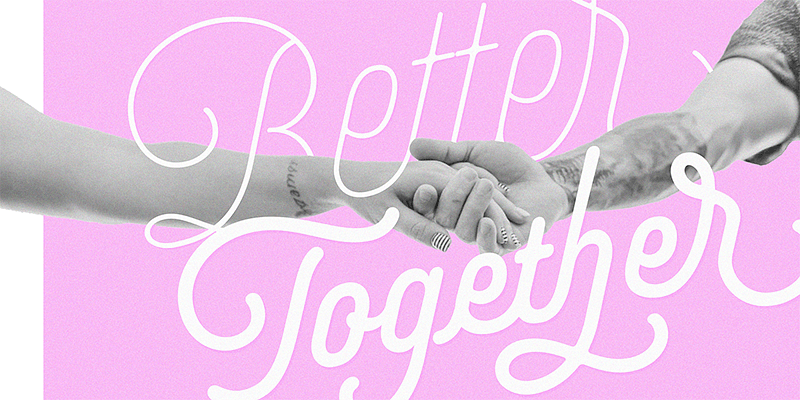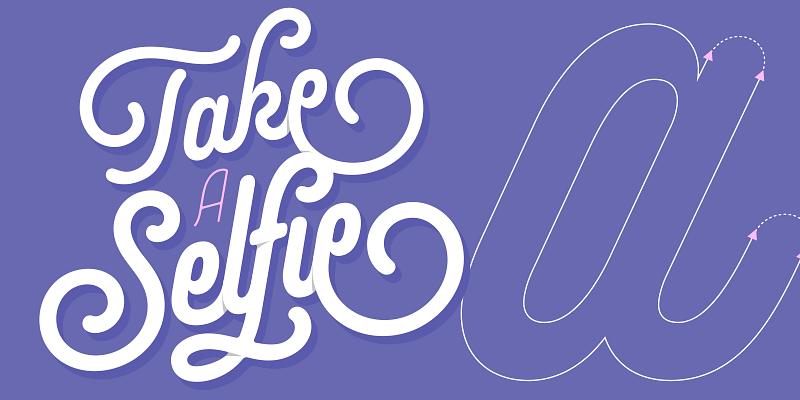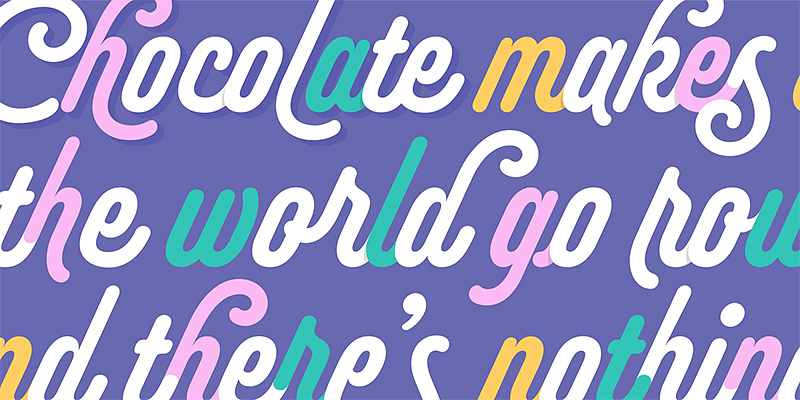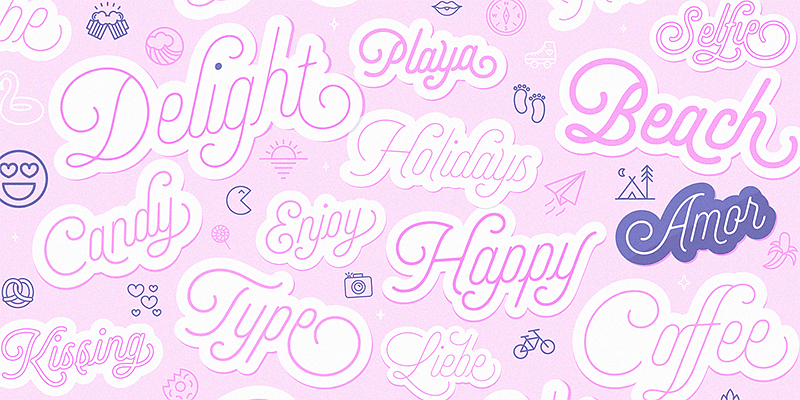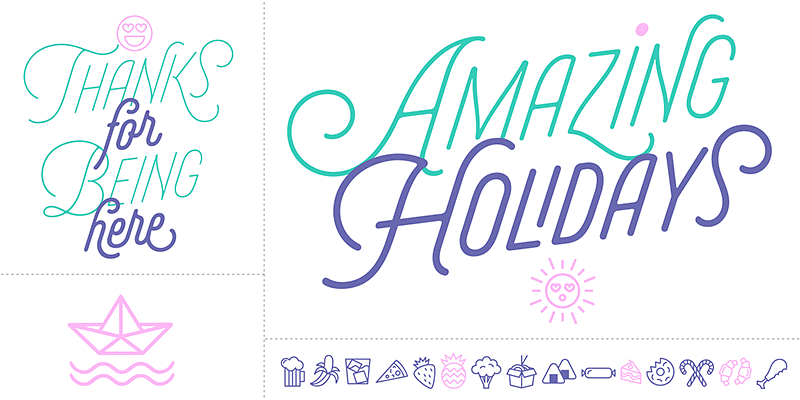
Sproviero Type ha creato un catalogo pluripremiato di font intricati, belli e moderni, senza lasciare alcun particolare inviolato. Il type designer Maximiliano Sproviero applica la sua passione per la calligrafia e la scrittura in una sorprendente raccolta di font individuali che sono fantasticamente decorati, fantasiosamente svolazzanti e incredibilmente originali. Qualunque sia il prodotto o il media, i font di Sproviero Type ti aiuteranno a porre le basi affinché i tuoi pensieri e le tue idee si trasformino in realtà.